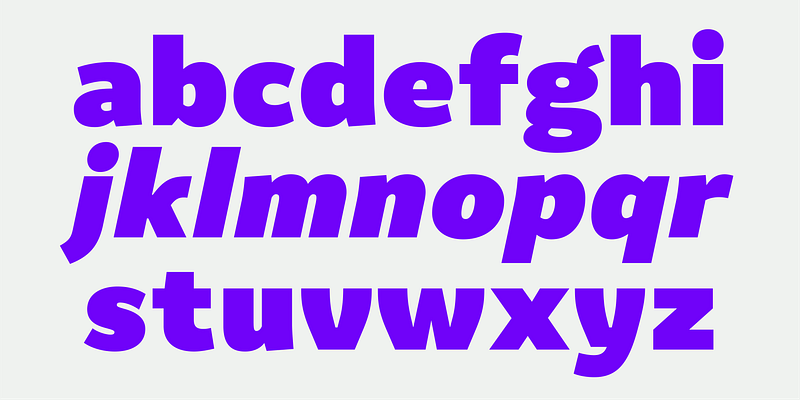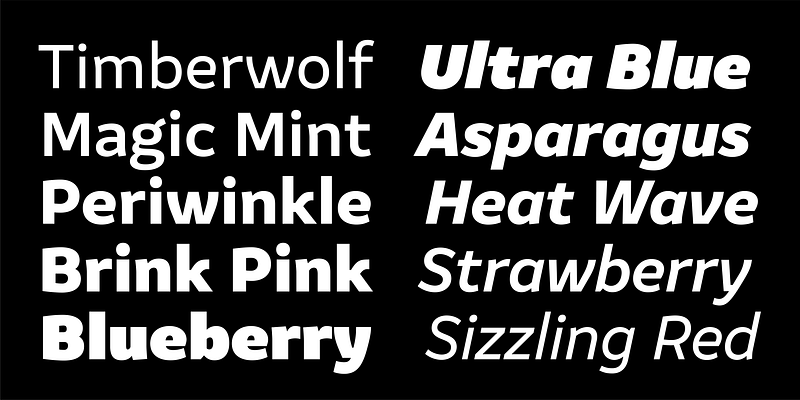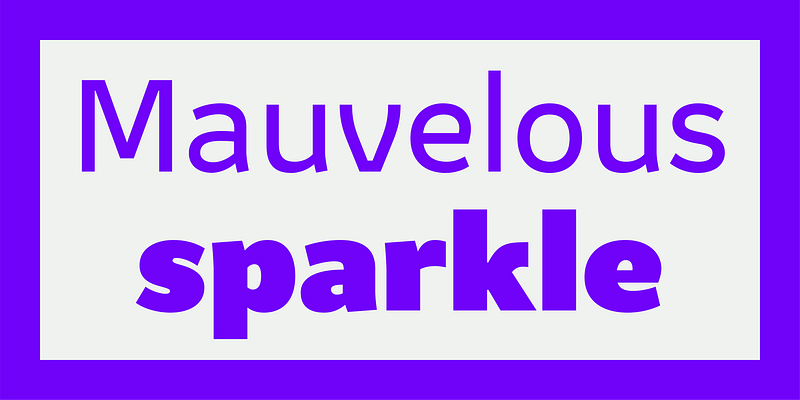
Amifer ist eine Familie von serifenlosen Schriften mit 10 Schnitten, die charaktervolle Buchstabenformen vereint, ohne die Klarheit und den zeitgemäßen Stil des Genres der serifenlosen Schriften zu beeinträchtigen.